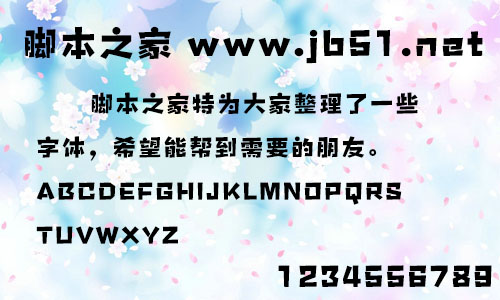
方正雅珠體是一款非?;顫?,歡樂,富有活力的字體,這款字體整體效果非常出色,有很強的視覺感,適合應(yīng)用于藝術(shù)設(shè)計領(lǐng)域,平面宣傳設(shè)計、兒童相關(guān)物品的宣傳等,需要的朋友可以前來本站下載。
方正雅珠體打破了傳統(tǒng)字體的筆形和結(jié)構(gòu),將筆畫以圖形化的手法進行處理,且富于變化,橫畫處理成粗壯的矩形,豎劃則近似于倒梯形,點、撇、捺、提也都處理成不規(guī)則的梯形,部分點畫處理成橢圓形,整體給人以稚拙、歡快、跳脫、無拘無束、充滿童趣的感覺,非常適合兒童相關(guān)的產(chǎn)品使用。
字體樣式
中文名 英文名
方正雅珠體簡體_纖 FZYaZhuTiS-GB_ExtraLight
方正雅珠體簡體_細 FZYaZhuTiS-GB_Light
方正雅珠體簡體 FZYaZhuTiS-GB_Regular
方正雅珠體簡體_準 FZYaZhuTiS-GB_Medium
方正雅珠體簡體_中 FZYaZhuTiS-GB_DemiBold
方正雅珠體簡體_粗 FZYaZhuTiS-GB_Bold
方正雅珠體簡體_大 FZYaZhuTiS-GB_ExtraBold
方正雅珠體簡體_特 FZYaZhuTiS-GB_Heavy